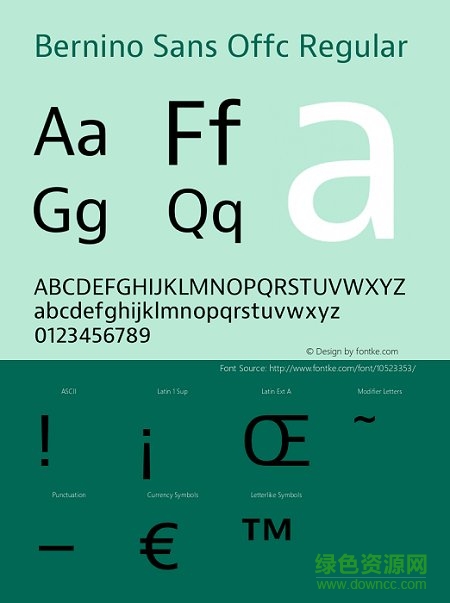
bernino英文字體
bernino是一款英文字體,字體端正有力風(fēng)格清爽大方,是在嚴(yán)謹(jǐn)內(nèi)容排版中使用較多的英文字體,給正本增加了更加嚴(yán)肅的氛圍,綠色資源網(wǎng)今日推薦!
bernino英文字體特色
為Bernino字體,內(nèi)容與標(biāo)題一致,很小尺寸也能很容易區(qū)分出應(yīng)得到的東西,平華且容易閱讀,讓人充滿了思考與聯(lián)想。
bernino系列字體介紹
bernino字體包括BerninoSansCondensed和Bernino Sans Offc Nr Lt Regular、Bernino Sans Offc Nr Exb等,字跡都比較深沉文章,有著十分出色的閱讀效果。